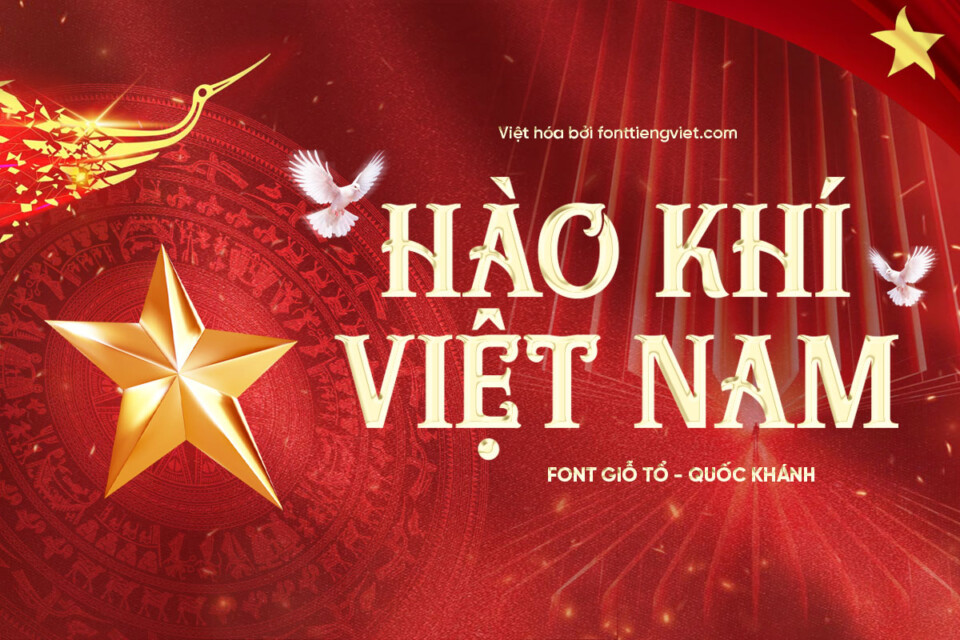
Font Việt hóa 1FTV VIP Hanora – Font Giỗ tổ Quốc Khánh mang đến giải pháp thiết kế trang trọng cho ngày lễ lớnÝ nghĩa của Font Việt hóa 1FTV VIP Hanora – Font Giỗ tổ Quốc Khánh trong thiết kế học đườngChào các thầy cô và các bạn học sinh, việc lựa chọn một Font Miễn Phí phù hợp cho các bài thuyết trình, báo tường hay băng rôn nhân ngày lễ lớn luôn là bài toán nan giải. Sự ra đời của bộ Font Việt hóa 1FTV VIP Hanora – Font Giỗ tổ Quốc Khánh đã mang đến một làn gió mới đầy ý nghĩa. Bộ chữ này sở hữu nét nét thanh nét đậm vừa uyển chuyển, vừa mạnh mẽ, thể hiện rõ tinh thần tự hào dân tộc và lòng biết ơn sâu sắc hướng về cội nguồn.Đặc điểm thiết kế độc đáo của bộ chữĐược tinh chỉnh tối ưu cho ngôn ngữ tiếng Việt, bộ chữ loại bỏ hoàn toàn lỗi hiển thị dấu cố hữu. Các đường nét được bo tròn tinh tế phối hợp cùng những nét hất mang đậm tính nghệ thuật. Nhờ vậy, bộ chữ cực kỳ phù hợp cho các tiêu đề lớn, khẩu hiệu hoặc lời tựa trang trọng trên các ấn phẩm truyền thông của nhà trường.Cách ứng dụng Font Việt hóa 1FTV VIP Hanora – Font Giỗ tổ Quốc Khánh hiệu quảĐể tạo nên một tác phẩm thiết kế đẹp mắt và thu hút, người dùng cần biết cách kết hợp màu sắc và bố cục sao cho hài hòa nhất.Lựa chọn màu sắc trang trọngĐối với các chủ đề tri ân lịch sử, việc kết hợp bộ chữ này với tông màu đỏ đô, vàng hoàng kim hoặc xanh đậm sẽ tôn lên vẻ đẹp quý phái, trang nghiêm cho toàn bộ tác phẩm.Sử dụng làm tiêu đề bài họcCác bạn học sinh có thể dùng bộ chữ làm tiêu đề cho các bài báo cáo môn Lịch sử hoặc Ngữ văn nhằm tăng tính sinh động và tạo ấn tượng mạnh mẽ với người xem.Kết luận và hướng dẫn tải font chữTóm lại, bộ Font Việt hóa 1FTV VIP Hanora – Font Giỗ tổ Quốc Khánh là một công cụ thiết kế tuyệt vời và không thể thiếu trong môi trường giáo dục hiện đại. Để sở hữu ngay bộ chữ đặc sắc này hoàn toàn miễn phí, quý thầy cô và các bạn học sinh hãy nhanh tay truy cập Font Miễn Phí, Font Việt Hóa, Font Việt hóa 1FTV VIP Hanora – Font Giỗ tổ Quốc Khánh để tải về bản cài đặt chuẩn nhất và bắt đầu sáng tạo nhé.
Font Việt hóa 1FTV VIP Hanora – Font Giỗ tổ Quốc Khánh